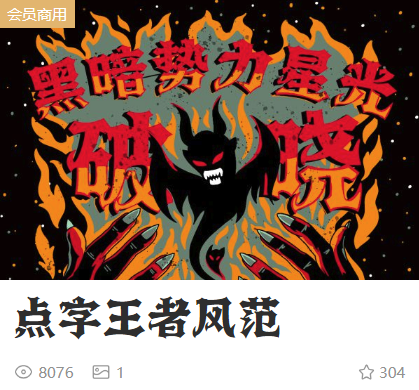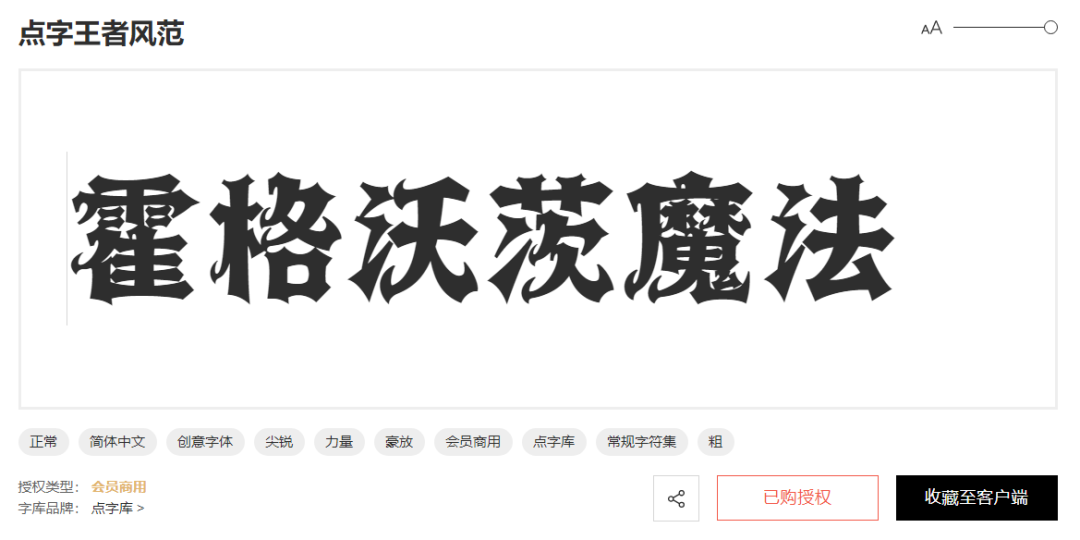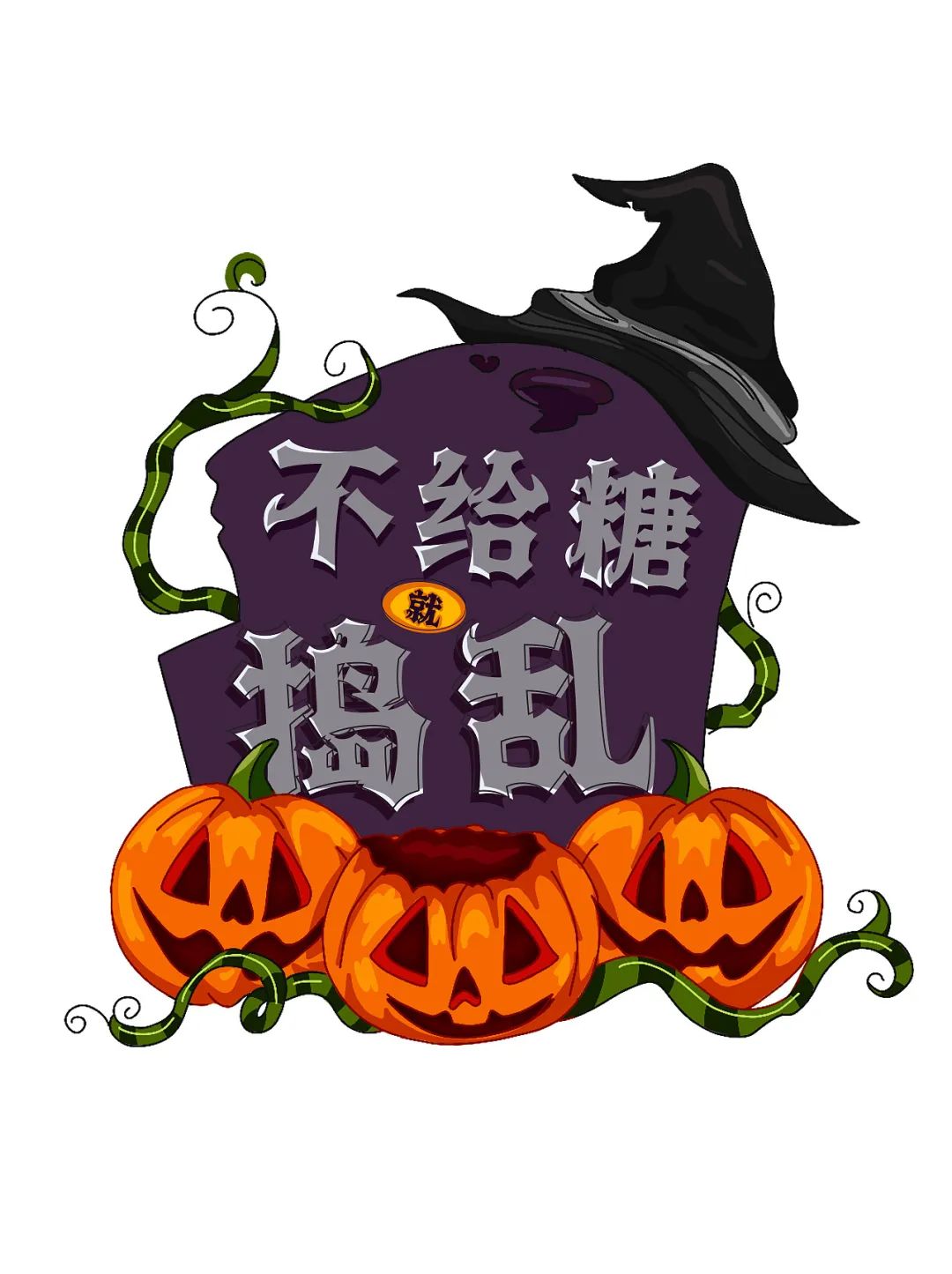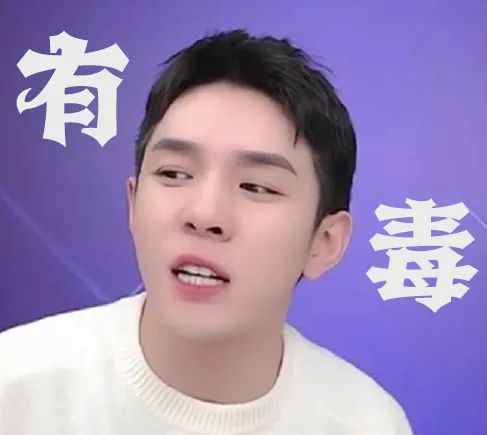
一款自带魔法的字体,这个万圣节必须拥有的字体
还有一周就是万圣节了,往年柚子都会推荐一些“鬼字”,比如气氛很足的汉仪万圣节体、汉仪小恶魔。
当然作为西方的节日,西文字体最是原汁原味~
不过今天这款字体,不光“很万圣节”,还“很哈利波特”,它就是点字王者风范!
字型偏哥特式,装饰感很强,一笔一画间,都渗透着“魔法”~
看柚子给你演示一下,如何点字成“魔”。
不疯魔不成活,点字王者风范运用在海报中,也是相当有内味了,快来沉浸式体验一下吧~